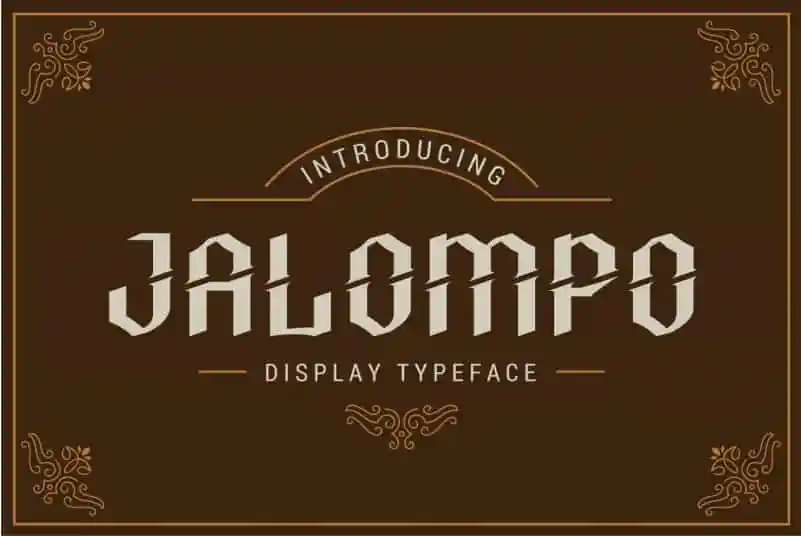
Jalompo Display Font é uma elegante tipografia para uso display que destaca caracteres com formas altas. Suportar sua marca ou projeto, esta fonte oferece a perfeição e consistência necessárias para estilos criativos e modernos. Com Jalamopo, você pode transmitir o impacto desejado em uma variedade de ambientes, desde websites até materiais impressos profissionais. Conhecida pelo seu designer Patria Ari Typestudio, essa fonte é ideal para quem busca qualidade e consistência em sua tipografia. Seja você um estilista digital ou editor gráfico, Jalamopo Display Font não apenas se destaca por suas formas altas, mas oferece a oportunidade de criar uma marca visual única e memorável.